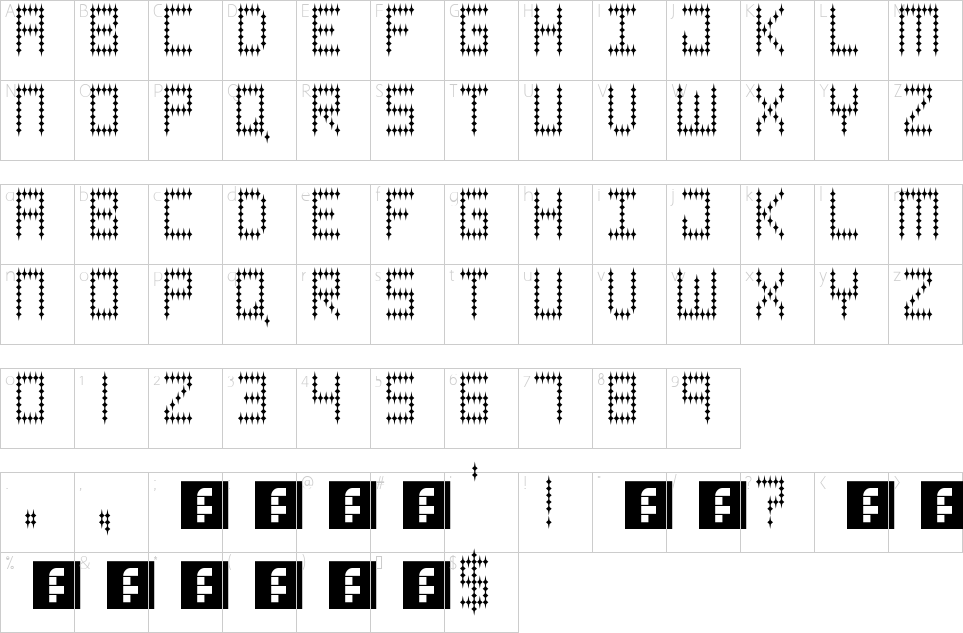
Descubra Jokerface, uma fonte de graça disponível para download tanto em Windows quanto em Mac. Essa fonte foi criada por Geronimo Fonts e já foi baixada por 2.668 pessoas. Jokerface oferece um visual único e original, perfeito para aqueles que buscam uma fonte inovadora para seus projetos. Adicione uma pitada de criatividade a seu próximo design com essa fonte grata. Não perca essa oportunidade de adquirir Jokerface e personalizar seus projetos de design com estilo único.